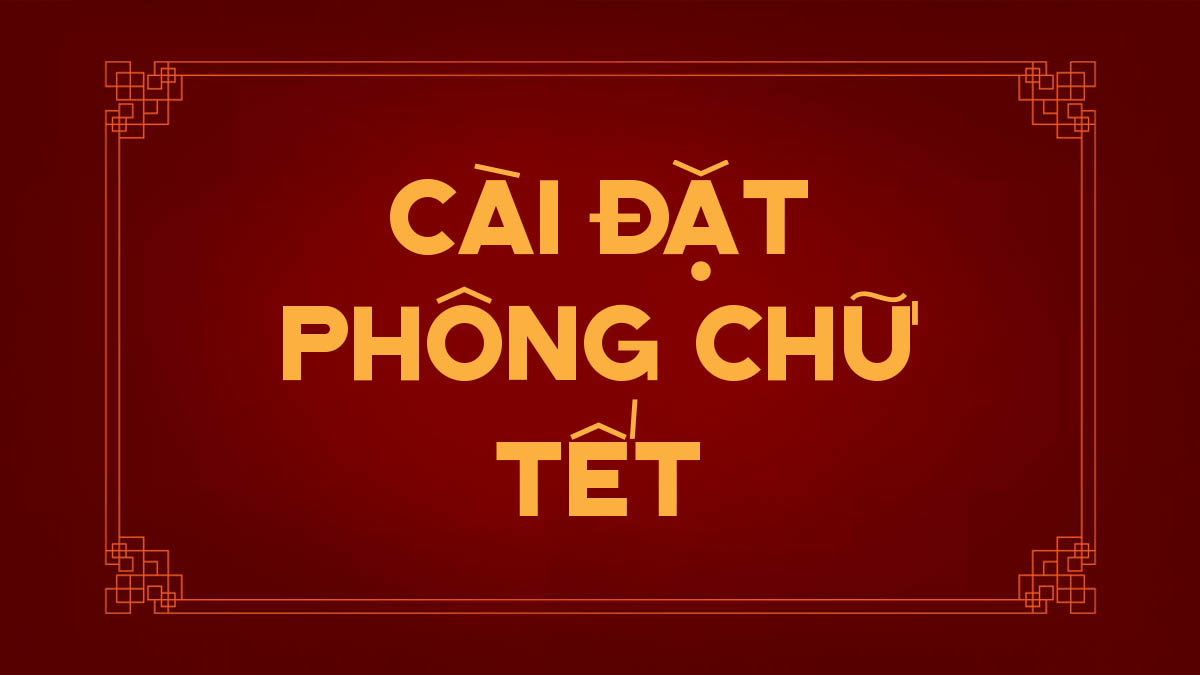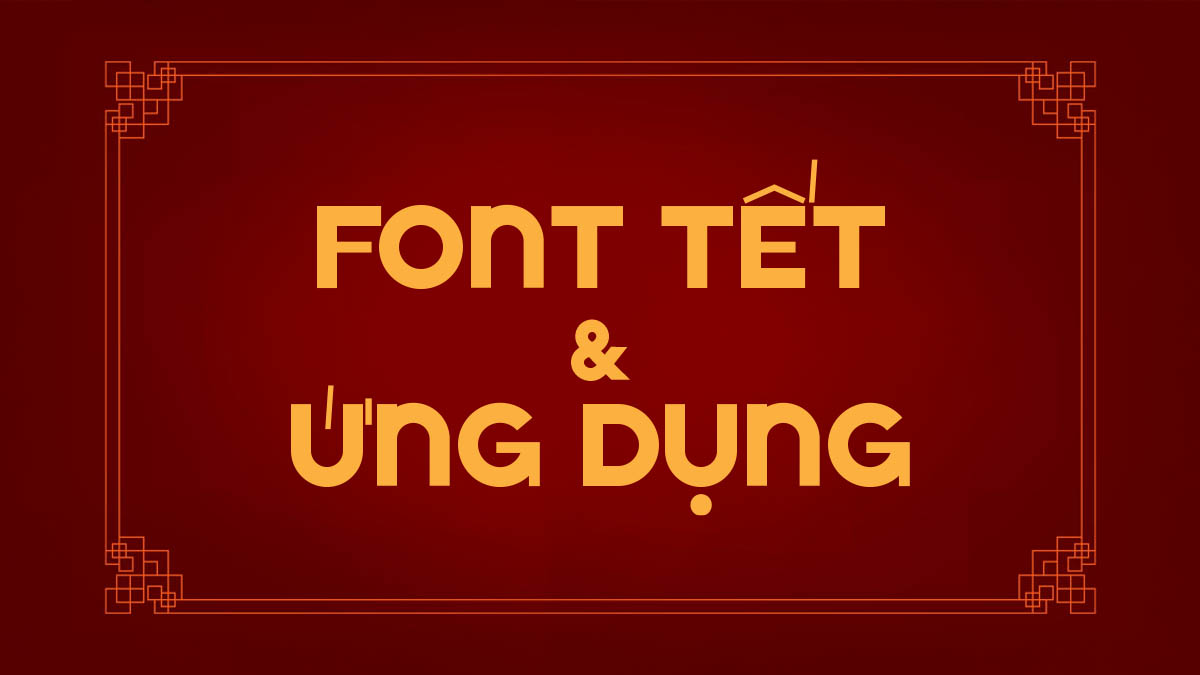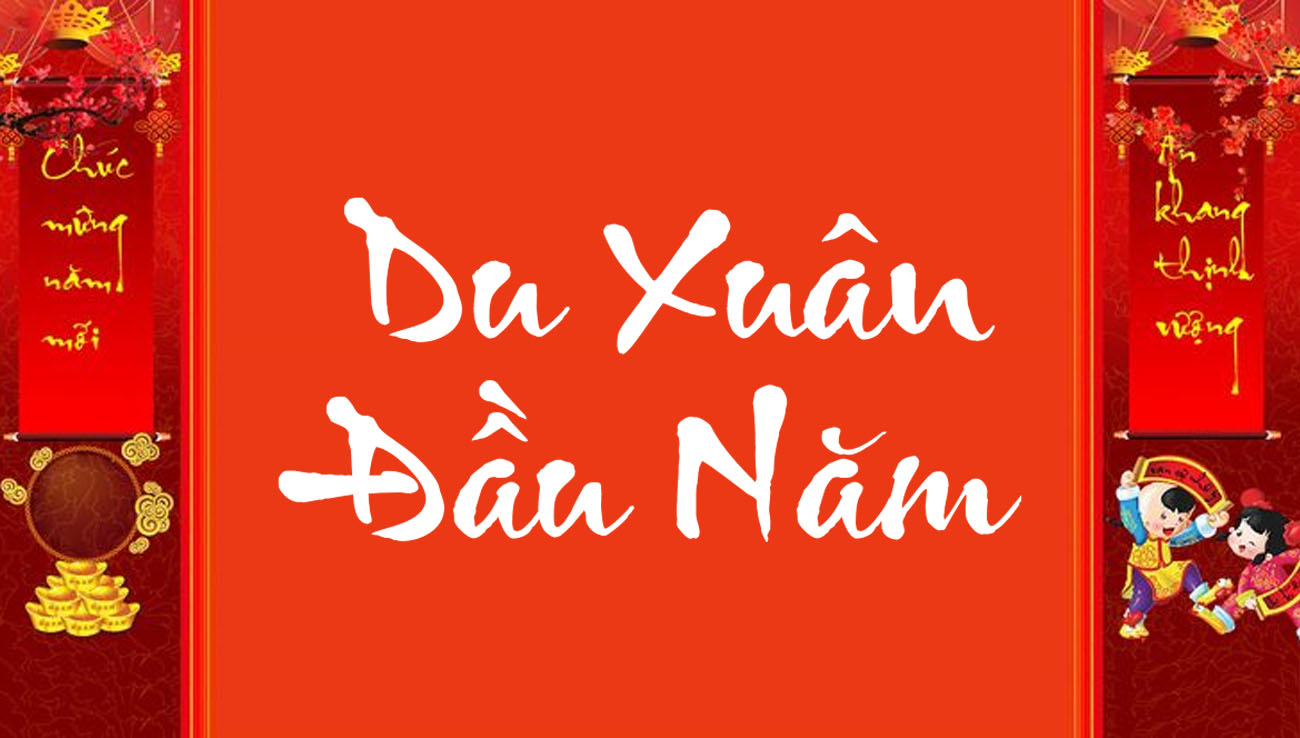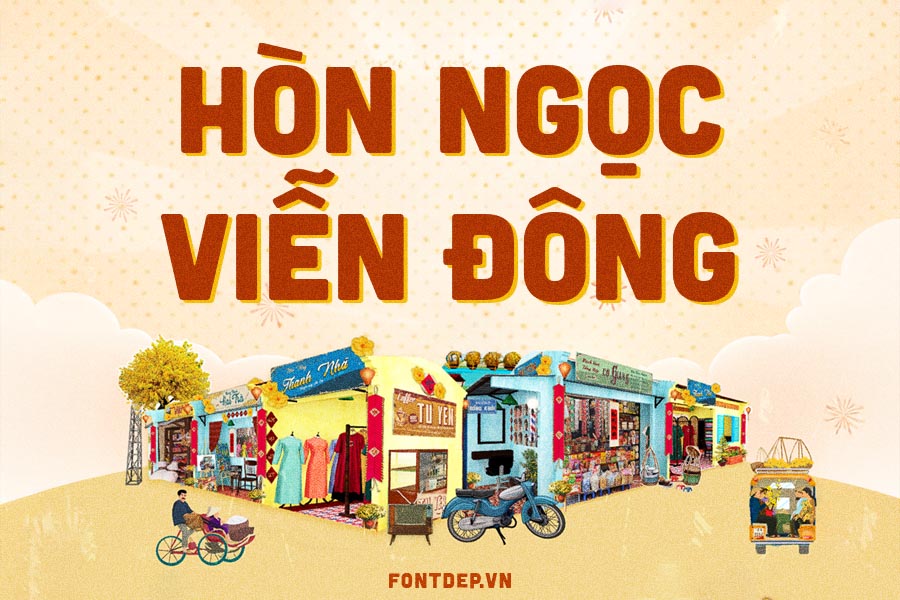
Dù bạn muốn thiết kế truyền thống, hiện đại hay hoài cổ, bộ sưu tập font chữ Tết Việt hóa 2026 này đều đáp ứng đầy đủ nhu cầu. Chọn đúng font sẽ giúp thiết kế trở nên cảm xúc, thu hút và đậm sắc xuân, từ thiệp chúc, poster, banner đến các ấn phẩm truyền thông online.